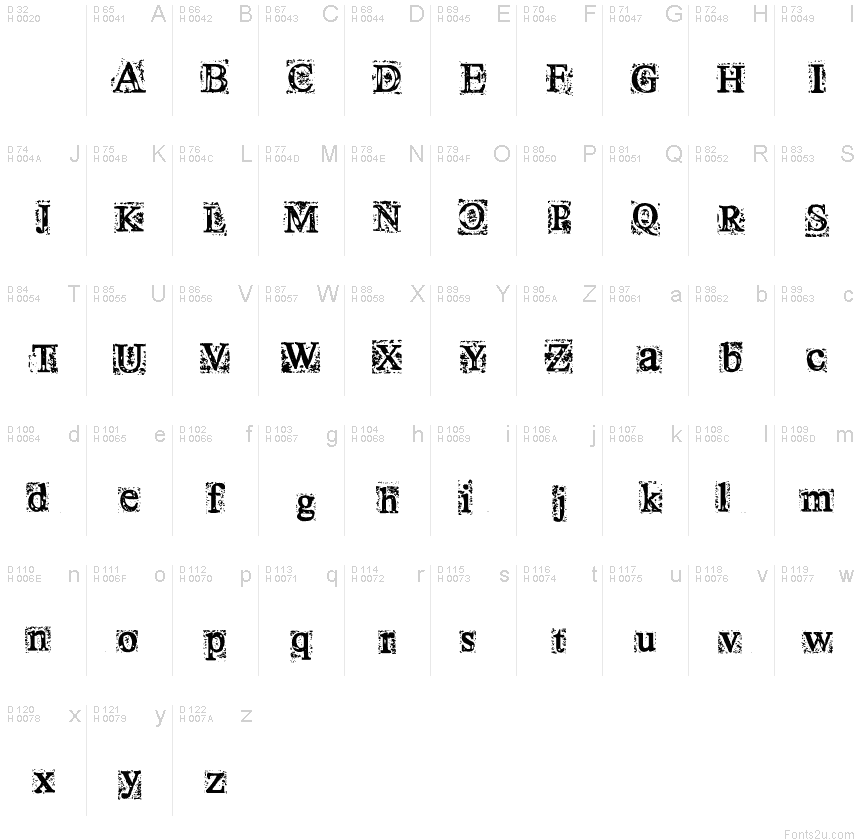
Times New Omen, darmowy szeryfowy krój pisma w stylu gazetowym od Data Becker, przejmuje znany głos Timesa i dodaje mu charakteru dzięki odpryskom, pęknięciom i nierównym przetarciom. Litery zachowują klasyczną, redakcyjną strukturę, ale dzięki zniszczonej teksturze sprawiają wrażenie wyciągniętych z uszkodzonego składu drukarskiego lub starej, podniszczonej gazety.
Takie połączenie sprawdza się w nagłówkach plakatów, okładkach fanzinów grozy, punkowych ulotkach, kartach tytułowych i okładkach albumów, gdzie rozpoznawalny szeryf potrzebuje bardziej surowego klimatu. Jako darmowy font, sprawdza się również w krótkich cytatach lub hasłach na okładkach, ponieważ klimat starej prasy jest wyczuwalny od razu, a efekt erozji robi całą robotę.